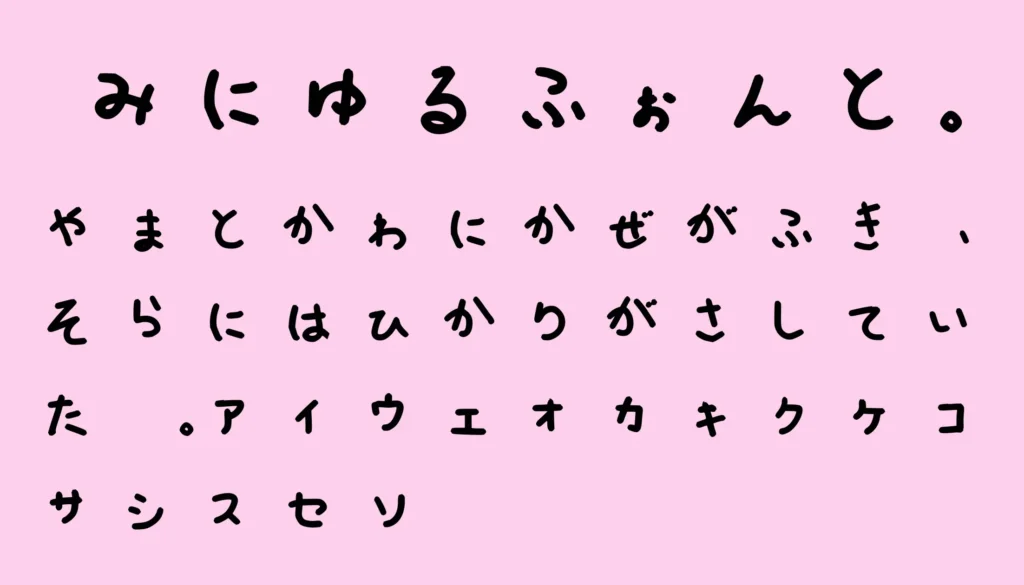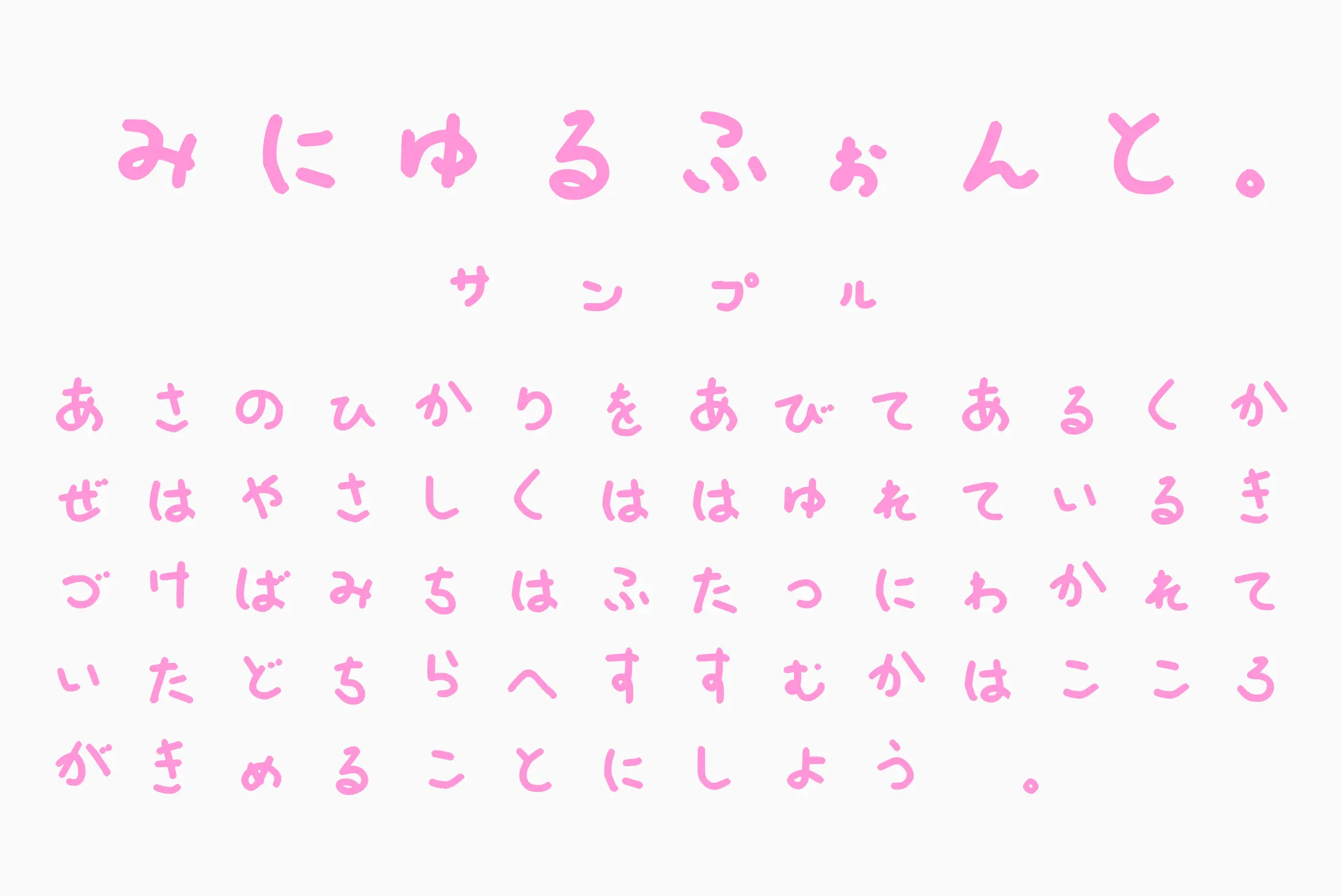
みにゆるふぉんと。 小さくてゆるい手書き文字を楽しめるフリーフォントです。ころんとした素朴な字形と、文字ごとに異なる手書きならではの揺らぎが魅力。短いメッセージや写真への一言、やさしくかわいい雰囲気のデザインにぴったりです。 カテゴリ OS Windows/Mac OS 形式 OpenType 収録文字 ひらがな 商用 商用利用可 配布サイト こちら ※利用規約は必ずお読みください フォントをダウンロードする 類似フォント一覧 マゾの手書き文字フォント まるぱんだ すこやかほーぷ 月縫い ニーロ丸ゴシック 平成女児★ふぉんと 手書きへにょ癖字 チューリップ